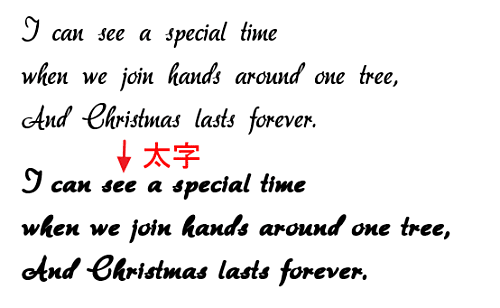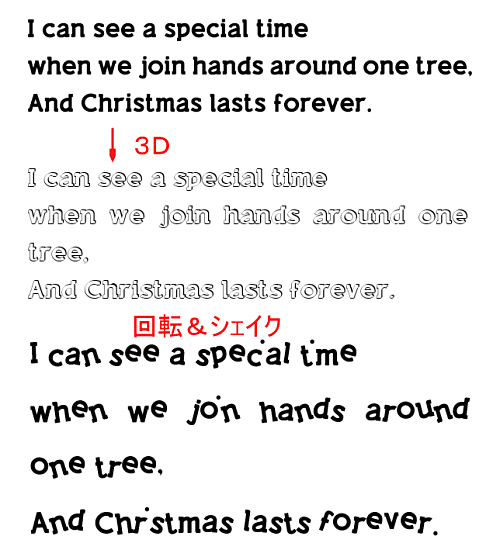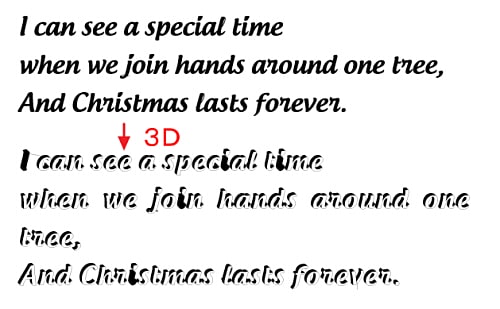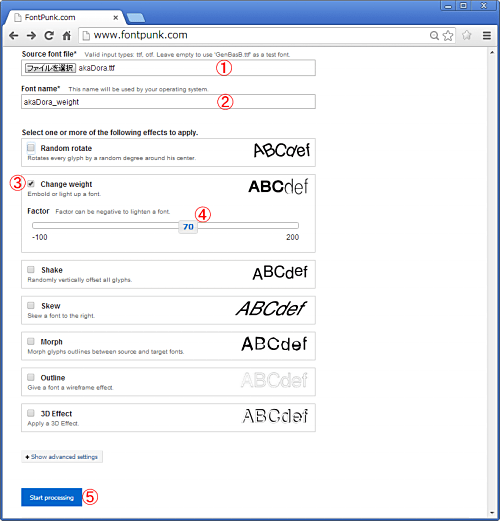
フォントファイルを加工するサービス
フォントファイルを、加工してくれちゃうサービス。
FontPunk.com(フォント・パンク)
フォントファイルそのものをいじって、新しいフォントファイルを作ります。
残念ながら、欧文フォントのみ対応。
「ファイルを選択」をクリックして、フォントファイルを指定します。
加工後のフォントに付けたいフォント名を、入力。
希望する加工に、チェック(複数選択OKです)。
スライドバーで、パラメーターを調整。
「Start Processing」ボタンを、クリック。
加工が完了したら、「Download_punked ~」ボタンをクリックして、
新しいフォントファイルを、ダウンロード。
フリーフォントで、試してみました。
1.「akaDora」を、太字(Change weight)に
2.「Androgyne」を、3D化(3D Effect)
このフォントのように、スクリプト・タイプ(筆記体)の場合は、
一部文字がうまく3D化できないことがあります。
今回は「i」がおかしくなりましたが、パラメーターによって別の文字になったり。
3.「Livestyle Marker M54」を、3D化と、回転&シェイク(Random rotate + Shake)
回転&シェイクでは、「i」が点だけになってしまいました。
「回転」や「シェイク」は、おもしろい。
「3D」や「アウトライン」は、文字色は透明になるので、
背景とうまく組み合わせると、いいかも。